유럽 타이포 기행 – London Typography tour.3
글. 김창식 Chang Sik Kim (그래픽디자이너, 미국 산호세대 그래픽디자인학과 학과장)
#1 영국 타이포그래피 기행 London Typography Tour ③
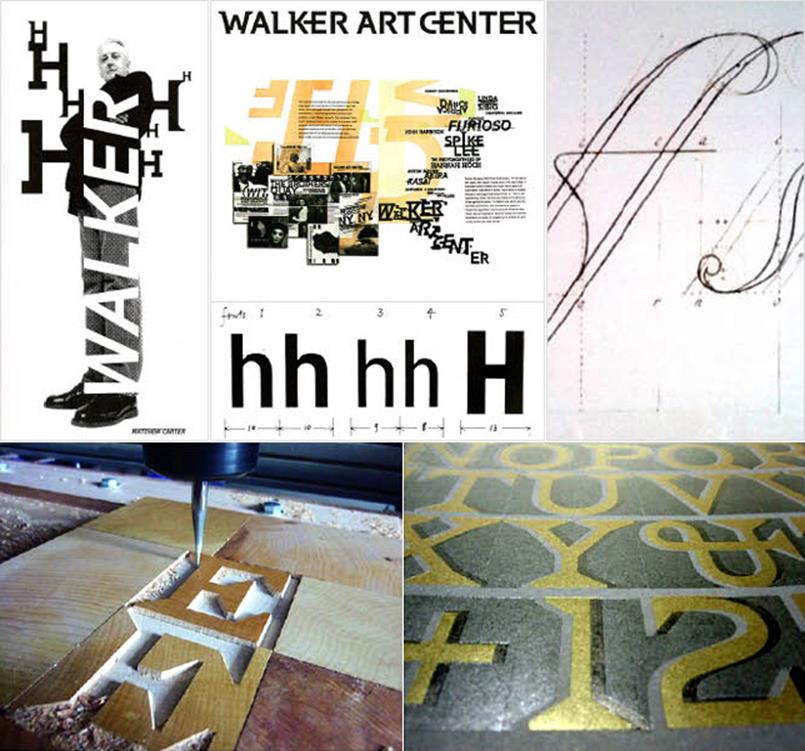
▲ 윗줄의 사진들은 Matthew Carter의 서체 작품들이고 아랫줄은 Hamilton Wood Type & Printing Museum에서 만든 그의 서체 목각 본이다.
1959년 발행된 타이포그래피 저널 The New Mechanick Exercises에 등장한 Matthew Carter는 제2의 Eric Gill로 불릴 만큼의 세상에 주목받기 시작하였다. 당시 꽤 유명했던 활자 세공가였던 아버지 Harry Carter의 영향을 받고 성장한 Matthew Carter는 Oxford 대학에 영문학 전공으로 입학했지만 지루한 고전, 문학에 흥미가 없었던 그는 아버지의 후원으로 타이포그래피계의 주요 인물들과 인연을 맺으며 본격적인 타이포그래피 관련 공부를 시작하였다. 하지만 주로 독학으로 연구하였고 마침내 1965년 미국 뉴욕으로 건너가 Mergenthaler Linotype에서 회사에서 일하게 되었다. 이때 Snell Roundhand, Helvetica Compressed, 그리고 Greek서체를 디자인하였다. Balliard서체는 그를 대표 하는 아름다운 서체이며 초기 그의 작업들은 주로 전통적 서체들의 부활에 초점을 두었다고 할 수 있다.
하지만 근래에 자신의 회사인 Carter & Cone 회사에서 개발한 Elephant, Mantinia, Sophia, Big Caslon, Alisal과 Walker등 다양한 서체들은 실용성보다는 좀 더 영감과 시각적 감흥을 주는 작품들이다. 그에 대하여 주목할 만한 점들은 단순한 서체디자이너가 아닌, 철학적, 심미적 접근, 그리고 문화 속에서의 타이포그래피를 논하는 통찰 능력과 박식한 인문학적 능력에서 비롯된 총제적 접근자로서의 타이포그래퍼라는 것이다. “movable type is now mutable type.”라는 그의 말에서 알 수 있듯이 끊임없는 서체에 대한 고민과 실험정신을 엿볼 수 있다. Matthew Carter는 종종 서체디자이너를 두 가지 부류로 논하곤 한다: 하나는 심미적 표현주의와 개성을 중시하는 형태의 탐구자들이고, 다른 하나는 그와 반대인 시각적 아름다움보다는 논리적이고 기능적이며 개념적인 면에 비중을 두는 개발자들이다.
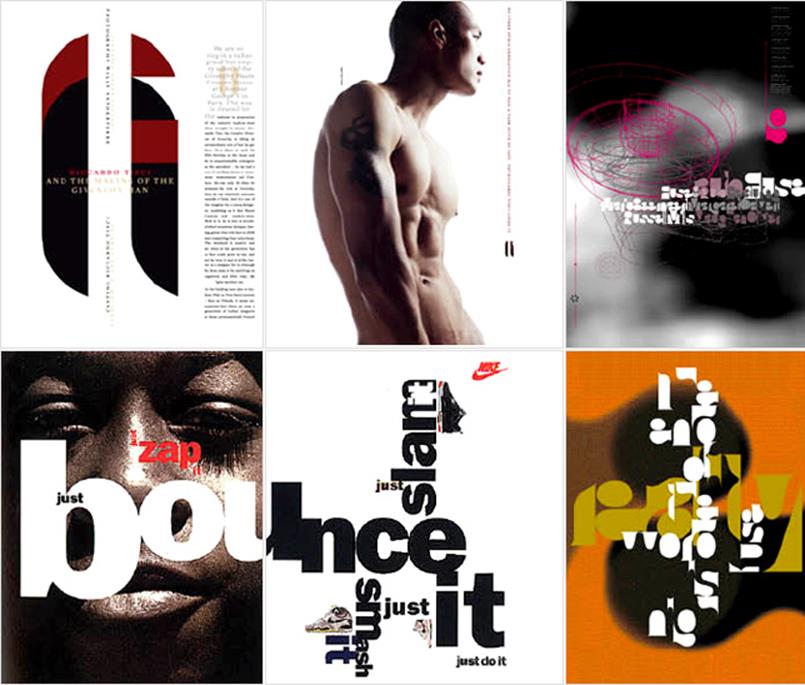
▲ 다양한 글꼴의 실험을 구사한 Neville Brody의 작품들
1987년 정도로 기억된다. 군 복무를 마치고 대학에 복학한 나는 당시에 서서히 불어오는 매킨토시 컴퓨터의 태풍을 직감하고 있었다. 대부분의 디자이너가 곧 다가올 타이포그래피와 출판 디자인의 대혁명적 세기말적 현상을 미쳐 짐작도 못하고 있는 사이에 서서히 하나둘씩 그 조짐의 징표가 수면위로 드러나기 시작하였다. 당시 적지 않은 수의 실험적인 디자이너들이 있었는데 Neville Brody가 바로 그 중에 한 사람이었다. 그의 타이포그래피에 대한 실험은 당시로써 많은 가능성을 제시하는 전조가 되었다. 글자와 이미지의 강렬한 상관관계를 극대화하였으며 볼드하고 강렬한 타이포그래피의 힘을 표출하였다. 대부분의 그의 글꼴들은 기하학적이고 반 추상적인 미래주의적 도형을 연상시키는 마치 암호화 된 일련의 코드를 연상시켰으며, 요즘 유행하고 있는 많은 디지털 타입의 전형을 보여주었다. 알카미스트의 암호 코드를 연상하게 하기도 했던 그의 타이포그래피의 새로운 미학은 디지털 시대로 대표되는 젊은 신세대 디자이너들에겐 가히 충격적인 영향력을 발휘하였다.
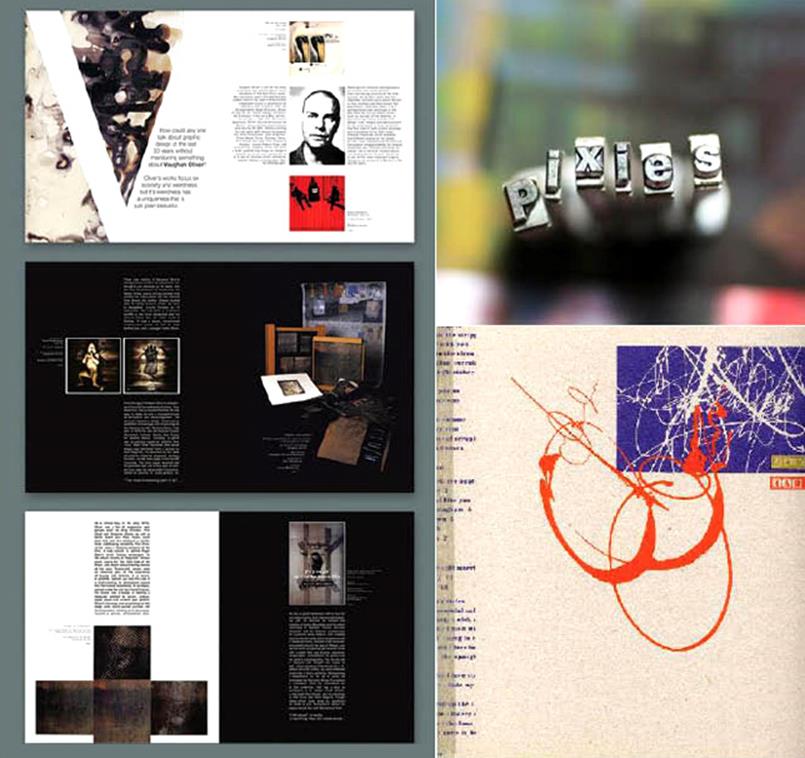
▲ Vaughan Oliver의 실험적인 타이포그래피 작업들
Vaughan Oliver은 런던 남쪽의 Epsom에 근거지를 두고 활동 중인 그래픽디자이너이다. Studios 23 Envelope으로 더 잘 알려진 그는 포토그라퍼인 Nigel Grierson과 함께 음반 레코드 회사 4AD에서 발행된 거의 모든 밴드들 (특별히 Cocteau Twins, Dead Can Dance, The Breeders, This Mortal Coil, Pale Saints, Pixies, and Throwing Muses)을 위한 디자인 (1982 년부터 1998년까지)을 제작하였으며, 록펑크의 새로운 시각적 이미지를 신비로운 사진과 실험적 타이포그래피로 시각화한 것으로 유명하다.
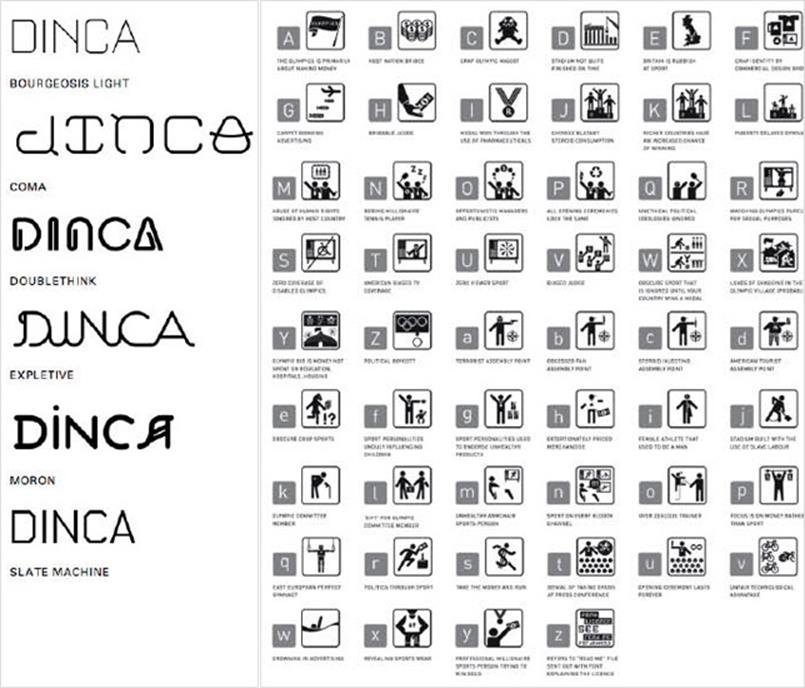
▲ 좌측은 Jonathan Barnbrook이 디자인한 다양한 글꼴들이며 우측은 해학적으로 사회현상을 픽토그램화한 타입페이스 OLYMPUKES이다.
Jonathan Barnbrook은 “디자인은 변화를 주도하는 다분히 정치적이고 문화적인 힘(영향력)을 가진 하나의 초자연적인 실체이다.” 라고 역설한다. 그래서 그의 대부분의 작품은 항상 정치적 이슈나, 기업 문화, 그리고 대중 소비문화의 쟁점을 주로 다룬다. 그의 작품 중 잘 알려진 2002년 David Bowie의 앨범 은 유명한 Priori font의 등장으로 그 만의 독특한 타이포그래피의 세계를 알리는 계기가 되었다. 지금까지 수많은 작업을 Adbusters Magazine을 통하여 하여왔으며 Virus Fonts를 비롯하여 다수의 실험적인 디스플레이 타입 (Bastard, Bourgeois, Coma, Doublethink, Echelon, Expletive Script, Infidel, Moron, Newspeak, Olympukes, Sarcastic, Slate Machine, and Tourette)을 제작하였다.
역설적인 그래픽과 타이포그래피의 조화를 다루는 그는 시각 메시지가 같은 소셜파워를 유감없이 발휘한다. 대부분 그가 만든 타입페이스는 사각형 모듈 안에 정형화된 틀과 일정한 획의 굵기. 그리고 직각에 가까운 획의 전환에 유기적 곡선을 맛을 가미한 묘한 분위기를 자아내는 fusion 스타일이다.
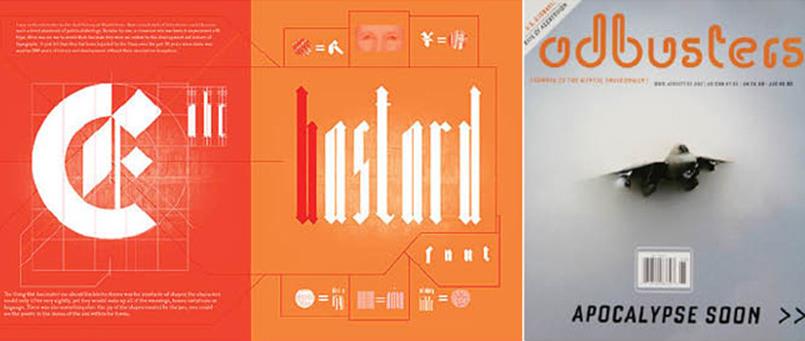
▲ 좌측은 2007년에 출간된 Barnbrook Bible의 한 스프레드 페이지이며, 우측은 ADBUSTERS COVER 디자인이다.
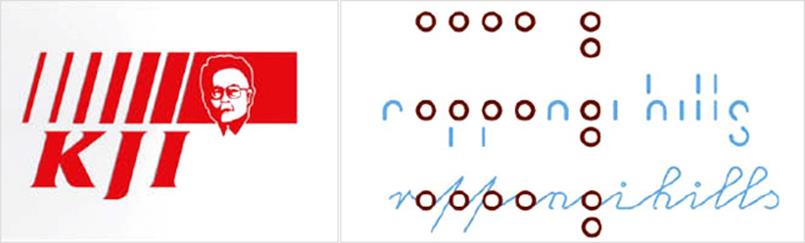
▲ 좌측은 정치적이고 사회적인 이슈를 다룬 Jonathan Barnbrook의 작품 중에 대표적인 예로 북한의 김정일을 모티브로 한 THE LITTLE FELLOW이다. KFC 로고와의 시각적 유사성을 이용한 풍자적 작품으로 독재자의 브랜딩화에 의한 은유적 비판을 시각화하였다. 우측은 2003년 개관한 일본 동경 록본기에 위치한 예술문화 타운 Roppongi Hills의 코퍼 레이트 아이덴티티. 여섯 그루의 나무를 상징하는 원형 패턴을 중심으로 영문 이름 자소의 유사성을 활용하여 생동감 넘치는 문화 예술의 복합건물로서의 상징성을 나타내는 포스트모던한 타이포그래피의 전형을 보여주는 작품이다.
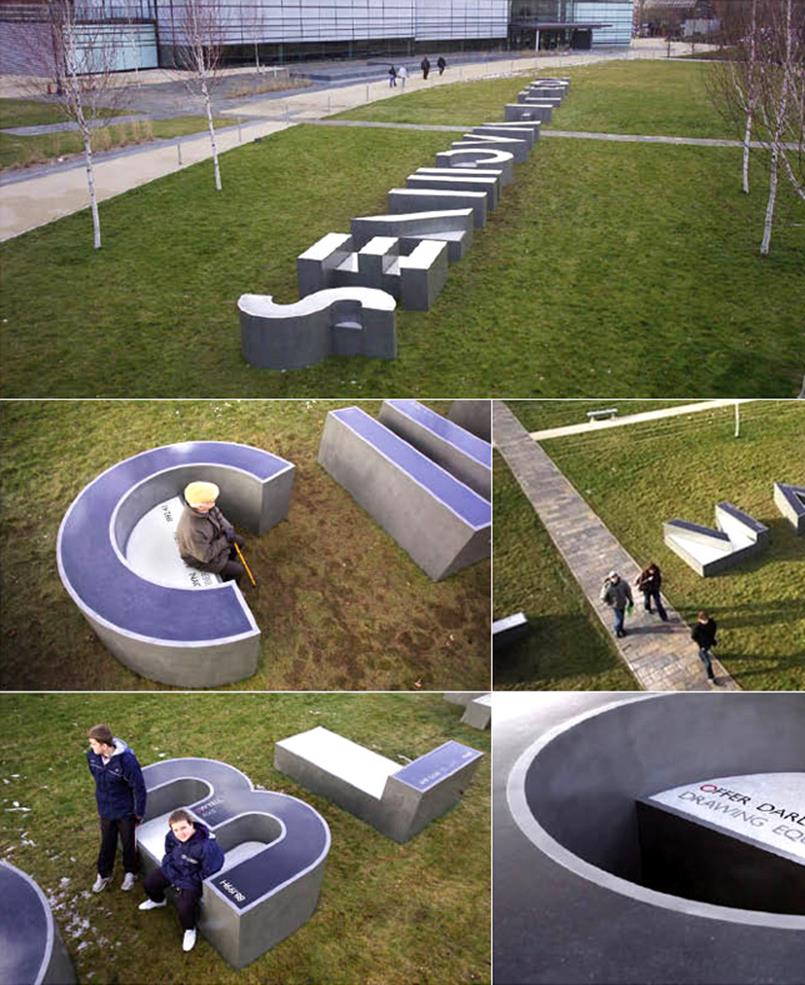
▲ Swansea에 있는 National Waterfront Museum을 위한 설치미술가 Gordon Young의 환경 타이포그래피 작품. 콘크리트와 그라나이트, 그리고 스테인레스 스틸로 구성한 조각 설치물은 예술과 타이포그래피 그리고 조경을 어우르는 작 품으로 전시장 내부와 야외 공원을 이어주는 개념적이고도 물리적인 매개물이다.
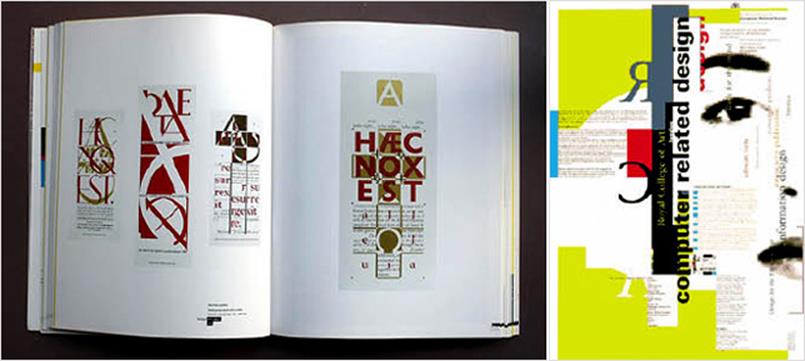
▲ why not associates의 초기 프린미디어 타이포그래피 작품들
90년대로 접어들면서 혜성처럼 등장한 영국을 대표하는 디자인 회사 why not associates는 말 그대로 글로벌 디자인 회사로서 급성장하여 국가 공공단체 및 기업체 등의 클라이언트와 함께 혁신적인 아이디어로 다양한 프로젝트를 진행하여왔다. 초기부터 지금까지 출판 및 공간 디자인 그리고 영상물에 이르기까지 끊임없는 타이포그래피의 실험을 통하여 무궁무진한 가능성과 이슈를 만들어왔다.
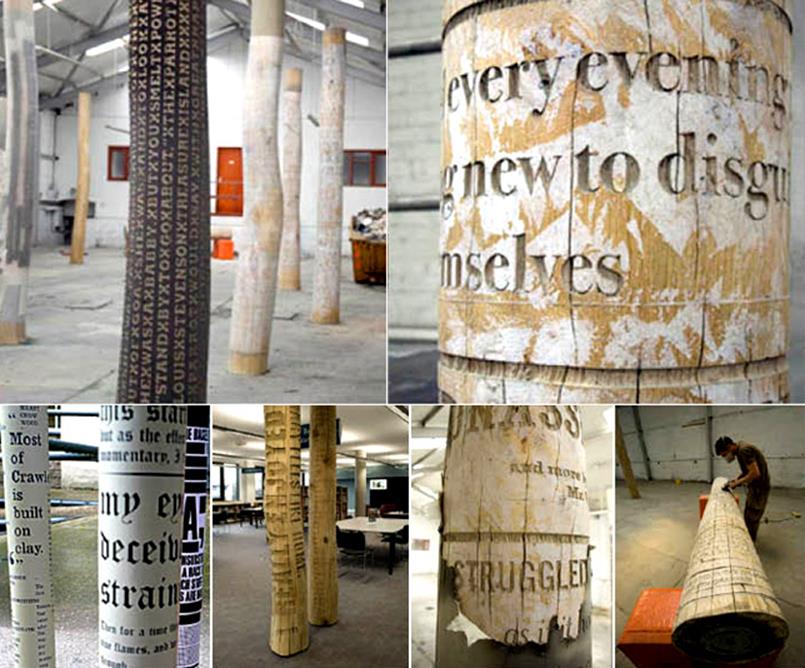
▲ 2009년 오픈한 Crawley Library을 위한 why not associates와 설치미술가 Gordon Young이 나무에 입체적으로 표현 한 타이포그래피 설치 작업으로 유기체로서의 정보와 지식의 성장을 암시하는 의미심장 한 작품이다.
▲ Why Not Associates이 기획하고 디자인한 환경 타이포그래피
▲ 함축적이면서도 재치 넘치는 런던 science museum의 로고와 1층 로비에서 2층 메인 전시장으로 올라가는 홀의 전경
▲ 좌측: 런던 시내에서 발견한 타이포그래피와 바이너리 코드를 이용한 흥미로운 광고물. 우측: 투명인간으로 분장한 거리의 행위 예술가. 그 아래는 자전거 타기를 홍보하는 캠페인으로 자전거 안장과 심장의 시각적 유사성을 활용했음
▲ 대영박물관 1층 로비에 설치되어있는 인포메이션 사인 시스템. 전시 주제물과 일반 공공시설물 안내 사인과의 조화가 두드러진다. 특히 재질을 상황과 환경에 맞게 사용함으로써 보다 효과적인 정보전달을 이룰 수 있도록 디자인하였다.
▲ RCA의 건물 전경과 대영박물관 1층 로비에 설치되어 있는 인포메이션 사인 시스템 세부 사진
Royal Mail은 “the greatest achievements of British design”이라는 명제 하의 Jason Tozer 사진과 HGV의 디자인으로 만들어진 기념 우표시리즈를 발행했다. 직설적이면서도 강렬하고 깔금하게 정리된 포맷과 사진 그리고 레이아웃이 돋보인다.
지금까지 앞으로 3회에 걸쳐 다룰 ‘현대 타이포그래피 매거진의 진수인 Baseline Magazine’, ‘글꼴 디자인 교육의 메카인 University of Reading’, 그리고 최근에 영국에서 가장 영향력 있는’폰트전문 제작회사 중 하나인 Dalton Maag Font Foundry’를 방문하여 실시했던 워크숍을 중심으로 다룰 글의 연재에 앞서 런던 타이포그래피 기행을 통하여 영국 타이포그래피의 이모저모를 살펴보았다. 앞서 언급한 학교와 스튜디오 방문을 중심으로 한 컬럼은 최근 영국 타이포그래피와 서체 디자인 현장 상황과 그들의 철학을 파헤쳐보는 대담 형식으로 게재될 것이다.